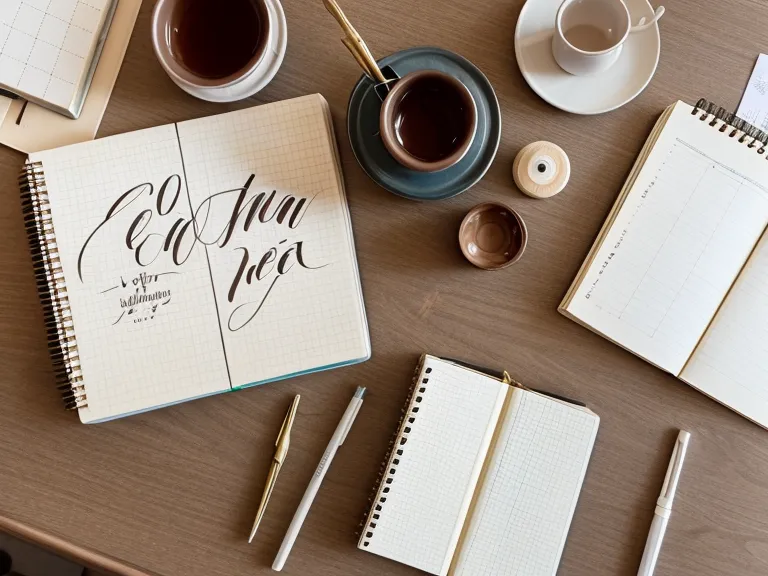
Drei von vier Anleitungen zur Textilgestaltung, die mir in den letzten Monaten untergekommen sind, erklären Handlettering auf Stoff mit genau einem Satz: Textil sei einfach gröberes Papier. Dieser eine Satz hat mir einen frisch geletterten Baumwollbeutel ruiniert, den ich nach einer schnellen DIY-Anleitung aus dem Netz beschriftet hatte. Was als Geschenk gedacht war, kam aus der Waschmaschine als grauer, verwaschener Fleck zurück – die Tinte war nicht bloß verblasst, sie war regelrecht in die umliegenden Fasern ausgeblutet. Seitdem prüfe ich jeden Handlettering-Kurs, der Stoff-Lettering verspricht, zuerst danach, ob er diesen Irrtum überhaupt anspricht oder ihn wie die meisten stillschweigend wiederholt.
Bevor der Beutel in der Maschine landete, hatte ich mich wochenlang nur theoretisch vorbereitet. Ein Sachbuch über Textildruck aus der Stadtbücherei Bonn lag aufgeschlagen neben mir, während ich mir stundenlang YouTube-Videos ansah, ohne ein einziges Mal selbst den Pinselstift in die Hand zu nehmen. Das kurze, satte Klacken, wenn ich die Kappe endlich vom Stift zog, kam erst, als der Schaden schon angerichtet war. Theorie ersetzt eben keine einzige geübte Bewegung.
Der Mythos vom groben Papier beim Stoff-Lettering
Fasern verhalten sich vollkommen anders als eine geschlossene Papieroberfläche. Auf Papier trägt die Spitze Farbe auf eine flache Ebene auf, auf Stoff trifft dieselbe Spitze auf ein Geflecht aus tausenden kleinen Fäden, die Farbe seitlich wegziehen, ungefähr so, wie ein Küchentuch verschütteten Kaffee nicht als Tropfen aufsaugt, sondern breit in alle Richtungen zieht. Genau dieses Wegziehen erklärt, warum ausgefranste Kanten entstehen, egal wie ruhig die Hand geführt wird. Das Prinzip der Druckkurve, das ich an anderer Stelle ausführlich durchgehe, gilt hier nur eingeschränkt. Auf Stoff zählt weniger, wie stark man drückt, sondern wie die Faser den Druck überhaupt aufnimmt. Ein Kurs, der Stoff einfach als Anhängsel zum Papierkapitel behandelt, spart sich genau diesen Unterschied und damit den eigentlichen Kern des Themas.
Neue Stoffe tragen ab Werk fast immer eine Appretur, die das gleichmäßige Aufnehmen der Farbe erschwert – waschen ohne Weichspüler vor dem ersten Versuch ist deshalb keine Empfehlung, sondern Pflicht. Reine Baumwolle hat sich in meinen eigenen Tests als einzig verlässliche Basis erwiesen, während Mischgewebe mit hohem Polyesteranteil die Farbe verlaufen lässt oder sie nach der ersten Wäsche fast komplett wieder freigibt. Welches Papier zu welchem Stift passt, ist übrigens ein eigenes Kapitel, das ich andernorts im Detail durchgehe, hier reicht die Feststellung, dass Stoff nach ganz anderen Regeln spielt als jede Papiersorte.
Warum funktioniert Ziehen besser als Drücken?
Nach inzwischen rund drei Jahren am Küchentisch würde ich sagen: Wer auf Stoff denselben Druck ansetzt wie auf Papier, presst die Spitze in die Zwischenräume der Webung, und die Kante franst aus, egal wie sauber die Buchstabenform sonst sitzt. Der Stift muss beinahe flach über die Oberfläche gezogen werden, fast so, als würde die Farbe nur auf die oberste Faserschicht gelegt. Ein Brush Pen nutzt sich auf rauem Canvas außerdem spürbar schneller ab als auf glattem Papier, wie stark halte ich in einem separaten Stifttest fest, aber für Stoff lohnt sich ohnehin ein robusteres Modell. Wie viele Übungsbögen es bis zu einer ruhigen Linie braucht, hängt stark vom jeweiligen Gewebe ab, dazu führe ich an anderer Stelle genauer Buch.
Beim Werkzeug selbst bin ich inzwischen von teuren Textilmarker-Sets abgekommen. Billige Acrylfarbe mit einem sehr feinen Pinsel gibt deutlich präzisere Kontrolle bei feinen Stoffstrukturen als jeder Filzstift, vor allem, wenn man die Viskosität mit einem Textilmedium anpasst, damit die Farbe nicht im Gewebe versinkt. Wer lieber ganz ohne Brush Pen arbeitet, kann die Faux-Calligraphy-Technik auf Stoff übertragen, das ist aber ein eigener Ansatz für sich. Ähnliche Grundsatzfragen zur Werkzeugwahl hatte ich schon bei Handlettering auf Glas lernen behandelt. Meine Kollegin Ursula, die grundsätzlich zuerst nach dem Preis-Leistungs-Verhältnis fragt, bevor sie überhaupt einen Kurs kauft, hat bei diesem Modul genau nachgehakt. Meine Antwort war unmissverständlich: Die Investition lohnt sich nur, wenn der Kurs auch die Fixierung erklärt und nicht nur hübsche Buchstaben zeigt.
Fixieren, ohne die Faser zu verbrennen
Die Trocknungszeit vor dem Fixieren wird auf vielen Verpackungen kurzgehalten, aber meine Erfahrung am Küchentisch zeigt: volle 24 Stunden Wartezeit senken das Risiko von Schattenbildung beim Bügeln erheblich. Zu früh gebügelte Stellen erkenne ich inzwischen sofort: ein leichter grauer Rand um die Buchstaben, der später nicht mehr weggeht. Auf Holz braucht Farbe eine ganz andere Art von Haftung als auf Faser, das hat mit Bügeltemperaturen nichts zu tun und ist ein eigenes Thema. Nach der dritten Bügelrunde in Folge zwickt bei mir übrigens der Nacken, aber auch das gehört auf ein anderes Blatt.
Fixiert wird am Ende über die Bügeltemperatur. Die Stufe 'Baumwolle', umgerechnet etwa 150 Grad, über mehrere Minuten reicht in der Regel aus, damit sich die Farbe dauerhaft mit der Faser verbindet. Eine Leserin, Andrea Helbig, hat mir vor einer Weile Fotos ihrer Übungsstücke geschickt und ganz genau nachgefragt, warum ihre Buchstaben beim Bügeln Schatten bekommen. Die Antwort war fast immer dieselbe: zu früh gebügelt, zu feucht war der Stoff noch. Ohne diese thermische Behandlung ist jede noch so saubere Schrift nach der ersten Wäsche wieder Geschichte.
Der Küchentisch bleibt das ehrlichste Testlabor
Die Faustregel, die bei mir hängen geblieben ist, lässt sich in drei Schritten zusammenfassen: vorbehandeln, ziehen statt drücken, und mindestens einen vollen Tag Geduld vor dem Bügeln. Ein Kurs, der einen dieser drei Punkte auslässt, liefert bestenfalls hübsche Buchstaben, aber kein waschechtes Ergebnis. Wer einfach drauflosschreibt, zahlt am Ende doppelt, für die Materialien und für die ruinierten Textilien, die noch mal von vorn beschriftet werden müssen.
Für kleine Flächen wie Etiketten oder schmale Beutelränder gilt zusätzlich, dass sich Buchstabengrößen anders verhalten als auf einem großen Kissenbezug, dazu habe ich bei Handlettering Kurs für kleine Schriften mehr notiert. Wie man mehrere Wörter oder ein Motiv am Ende auf der Fläche anordnet, ist wieder eine eigene Frage der Komposition, die mit der Stofftechnik selbst wenig zu tun hat. Ob sich das vorab am Tablet layouten lässt, bevor die Farbe überhaupt auf den Stoff kommt, ist ebenfalls ein eigenes Kapitel, das ich hier nicht aufmache.
Mein Mann hat neulich nach der Geburtstagskarte gefragt, die frisch auf dem Küchentisch lag, und wollte wissen, wie lange ich dafür gebraucht habe, kürzer jedenfalls als jeder einzelne der inzwischen 15 Stoffbeutel, die bei mir fertig geworden sind. Meine Finger sehen an solchen Wochenenden aus, als hätte ich mit bloßen Händen einen Tintenfisch gefangen, und die Küchentischdecke hat auch schon bessere Tage gesehen. Der Unterschied zwischen Karte und Stoffbeutel bleibt trotzdem derselbe: Papier verzeiht fast alles, Faser verzeiht nur, was vorher richtig vorbereitet wurde. Wer also seine Garderobe oder ein Geschenk verschönern will, sollte die Zeit lieber in die Materialkunde stecken als in ein weiteres Video.